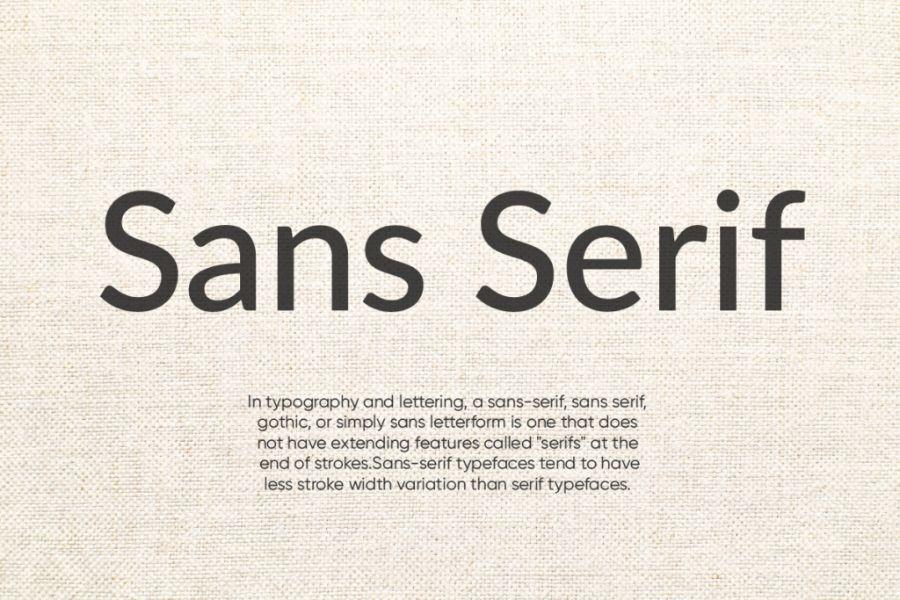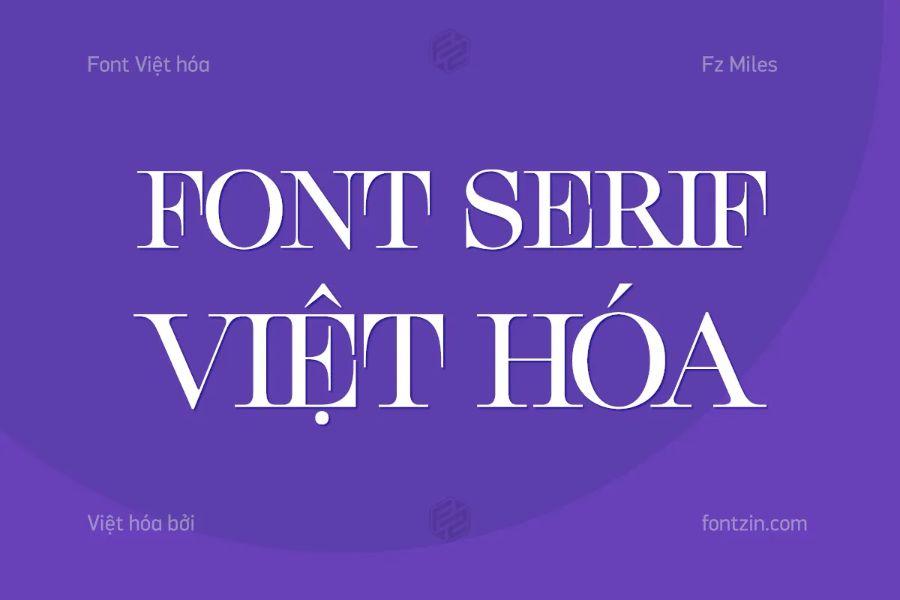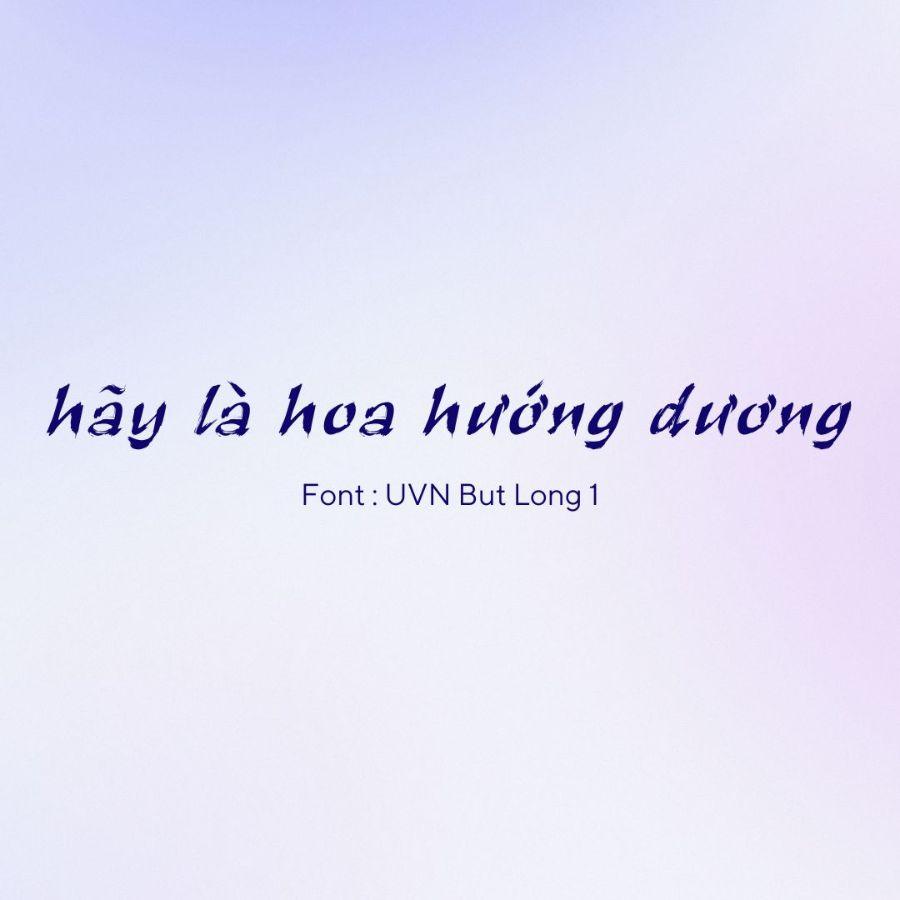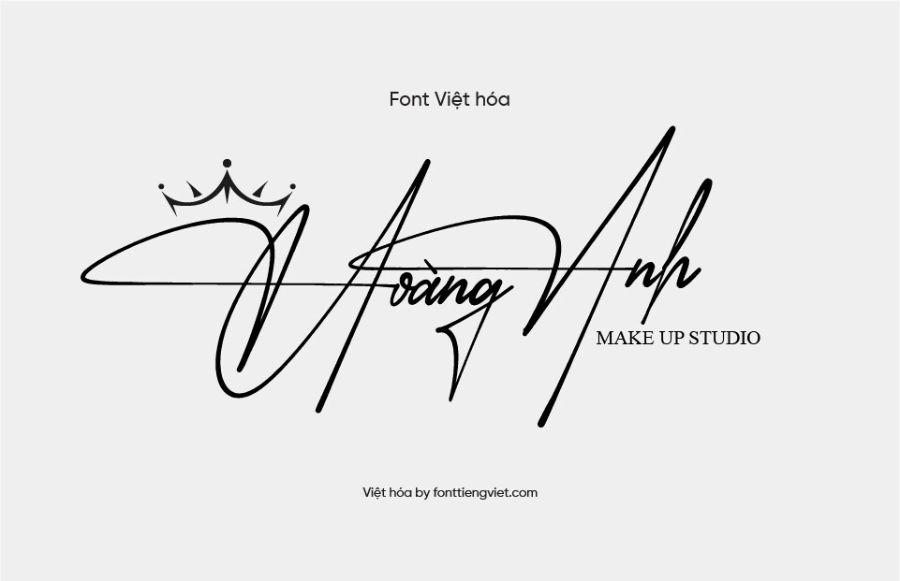
Kho Báu Font Việt Hóa 2025: Hướng Dẫn & Gợi Ý Phối Đỉnh Cao
Khám phá các loại font Việt hóa đẹp trên Canva. Danh sách đầy đủ các phông chữ hỗ trợ tiếng Việt có dấu, dễ đọc, bắt mắt và phù hợp cho thiết kế ấn phẩm chuyên nghiệp.
Đối với bất kỳ nhà thiết kế nào tại Việt Nam, dù là chuyên nghiệp hay nghiệp dư, hành trình sáng tạo trên Canva đôi khi giống như một cuộc đi tìm kho báu đầy thử thách. Bạn tìm thấy một font chữ quốc tế với đường nét mê hoặc, nhưng khi gõ tiếng Việt, "cơn ác mộng" ập đến: dấu nhảy lung tung, ký tự biến dạng, chữ "đ" trở thành một khối vuông vô hồn. Sự thất vọng này không chỉ làm gián đoạn dòng cảm hứng mà còn khiến ấn phẩm của bạn trông thiếu chuyên nghiệp và cẩu thả.
Bài viết này, cập nhật cho năm 2025, sẽ là tấm bản đồ chi tiết nhất dẫn bạn đến với "kho báu" font Việt hóa trên Canva. Chúng ta sẽ không chỉ liệt kê, mà còn phân loại, phân tích tính cách và gợi ý những cách phối hợp đỉnh cao để bạn tự tin làm chủ nghệ thuật typography trong từng sản phẩm của mình.
1. Tại Sao Lựa Chọn Font Việt Hóa Lại Quan Trọng Hơn Bạn Nghĩ?
Canva sở hữu một thư viện hàng ngàn font chữ, nhưng việc tìm ra những "viên ngọc" được Việt hóa chỉn chu, đẹp mắt và phù hợp với tinh thần thương hiệu Việt là một nghệ thuật. Nhiều người dùng thường chỉ quanh quẩn với vài cái tên quen thuộc như Montserrat hay Open Sans. Tuy nhiên, ẩn sâu trong kho tàng đó là vô số font Việt hóa đẹp mắt khác mà có thể bạn chưa từng biết đến, đủ sức nâng tầm thiết kế của bạn từ "tạm ổn" lên "xuất sắc".
Trước khi đi vào danh sách cụ thể, chúng ta cần hiểu rõ tầm quan trọng chiến lược của việc sử dụng font chữ được Việt hóa chuẩn. Đây không chỉ là vấn đề kỹ thuật, mà còn là yếu tố cốt lõi của truyền thông hiệu quả.
• Đảm bảo Tính Toàn Vẹn Của Thông Điệp: Một font chữ lỗi sẽ phá vỡ hoàn toàn dòng chảy thông tin. Người đọc sẽ bị phân tâm bởi các ký tự sai lệch thay vì tập trung vào nội dung bạn muốn truyền tải. Thông điệp của bạn, dù sâu sắc đến đâu, cũng sẽ mất đi giá trị.
• Thể Hiện Sự Chuyên Nghiệp và Tôn Trọng: Một thiết kế sử dụng font Việt hóa chỉn chu cho thấy bạn thực sự đầu tư vào sản phẩm của mình và tôn trọng khán giả Việt Nam. Ngược lại, font lỗi tạo ra ấn tượng về một thương hiệu cẩu thả, thiếu chuyên nghiệp và không đáng tin cậy.
• Tối Ưu Hóa Trải Nghiệm Người Đọc (UX): Một font chữ dễ đọc, hiển thị dấu rõ ràng giúp mắt người xem lướt qua văn bản một cách mượt mà. Điều này đặc biệt quan trọng với các đoạn văn bản dài trên website, blog, hay các ấn phẩm in ấn, giúp tăng thời gian tương tác và khả năng ghi nhớ thông tin.
• Xây Dựng Nhận Diện Thương Hiệu Nhất Quán: Khi đã chọn được một bộ font Việt hóa ưng ý, bạn có thể tự tin sử dụng chúng trên mọi ấn phẩm, từ logo, website, bài đăng mạng xã hội cho đến bao bì sản phẩm. Sự nhất quán này chính là chìa khóa để xây dựng một hình ảnh thương hiệu mạnh mẽ và dễ nhận diện.
2. "Bí Kíp" Tìm và Lọc Font Hỗ Trợ Tiếng Việt Trực Tiếp Trên Canva
Trong quá trình thiết kế trên Canva, việc lựa chọn font chữ hỗ trợ tiếng Việt là yếu tố quan trọng để đảm bảo tính thẩm mỹ và sự chính xác trong nội dung. Để tìm và lọc các font chữ phù hợp, người dùng có thể tận dụng tính năng tìm kiếm trực tiếp trên nền tảng này bằng cách nhập từ khóa liên quan hoặc thử nghiệm với các font phổ biến đã được xác minh hỗ trợ tiếng Việt.
Ngoài ra, việc kiểm tra kỹ từng font trước khi áp dụng vào thiết kế sẽ giúp tránh các lỗi hiển thị không mong muốn, đồng thời tối ưu hóa trải nghiệm sáng tạo của bạn trên Canva.Tuy nhiên, có một phương pháp thủ công nhưng cực kỳ hiệu quả để kiểm tra bất kỳ font chữ nào:
1. Mở Thiết Kế và Thêm Hộp Văn Bản: Vào thiết kế của bạn, chọn mục "Văn bản" (Text) ở thanh công cụ bên trái và thêm một hộp văn bản bất kỳ.
2. Gõ Đoạn Văn Bản Tiếng Việt Đầy Đủ Dấu: Hãy gõ một câu chứa các ký tự và dấu phức tạp của tiếng Việt. Một câu kiểm tra kinh điển là: "Nguyễn Thị Thúy Hằng là một kỹ sư phần mềm xuất sắc." Câu này chứa cả nguyên âm có dấu, chữ "đ", và các thanh điệu khác nhau.
3. Mở Menu Font Chữ: Nhấp vào hộp văn bản, bạn sẽ thấy tên font hiện tại ở góc trên bên trái. Nhấp vào đó để mở danh sách toàn bộ font chữ.
4. Rê Chuột và Xem Trước Trực Tiếp: Bây giờ, bạn chỉ cần từ từ rê chuột qua danh sách các font chữ. Hộp văn bản của bạn sẽ tự động thay đổi theo font bạn đang trỏ vào. Đây là bước quan trọng nhất. Hãy quan sát kỹ câu văn của bạn.
• Nếu font chữ hiển thị đầy đủ, rõ ràng và đẹp mắt, đó là font được Việt hóa tốt.
• Nếu bất kỳ ký tự nào (như "ý", "ằ", "ữ", "đ") bị biến dạng, thay thế bằng font khác hoặc hiển thị thành ô vuông, hãy bỏ qua font đó ngay lập tức.
3. Kho Báu Font Sans-serif (Không Chân) Việt Hóa: Đa Dụng & Hiện Đại
Kho báu font sans-serif Việt hóa mang đến sự đa dụng và hiện đại, phù hợp với nhiều mục đích thiết kế từ ấn phẩm truyền thông, thương hiệu, đến giao diện người dùng. Với đặc điểm không chân, các font chữ này tạo cảm giác gọn gàng, tối giản nhưng vẫn giữ được nét tinh tế và chuyên nghiệp.